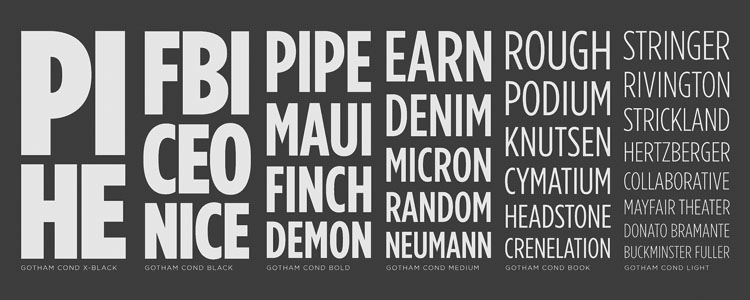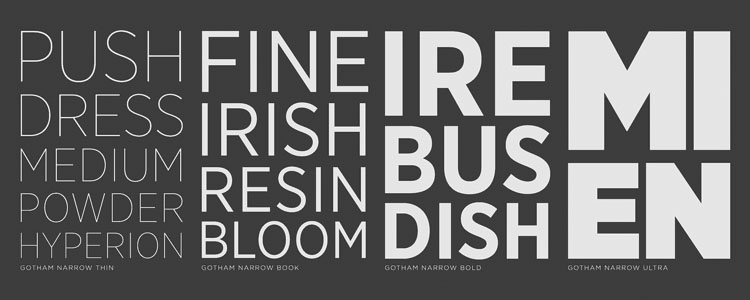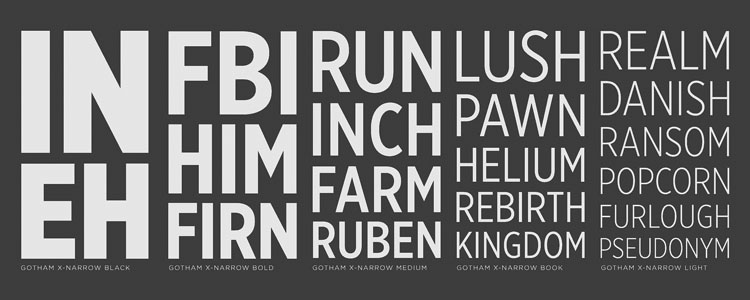
Gotham Narrow, Extra Narrow und Condensed (H&FJ)
A hard-working typeface now works even harder. Meet Gotham Narrow, a space-saving sans serif designed for small sizes and settings, and Gotham Extra Narrow, a collection of compact fonts for text and display alike. Also at H&FJ, fourteen new styles of Gotham Condensed, now featuring an expanded range of weights from thin to ultra, each now accompanied by a matching italic. Now with tabular figures, fractions, and our Latin-X® character set for expanded language support.
Finde ich auch - mit der Condensed konnte ich
noch nie was anfangen! Aber die Narrow ist
eine sehr gute Ergänzung zur normalen und recht
breiten Gotham.
Schöön, noch mehr Gotham zu kriegen! Ansonsten schließe ich mich meinen Vorrednern an, die ganz schmalen bringen den «Spirit» irgendwie nicht so ganz rüber, zumindest auf Anhieb. Aber kann ja praktisch sein, sowas zu haben, man weiß ja nie :)
Ja, die Condensed scheinen ausserhalb zu liegen, die Narrows sehen auch für mich passend(er) aus. Schön!